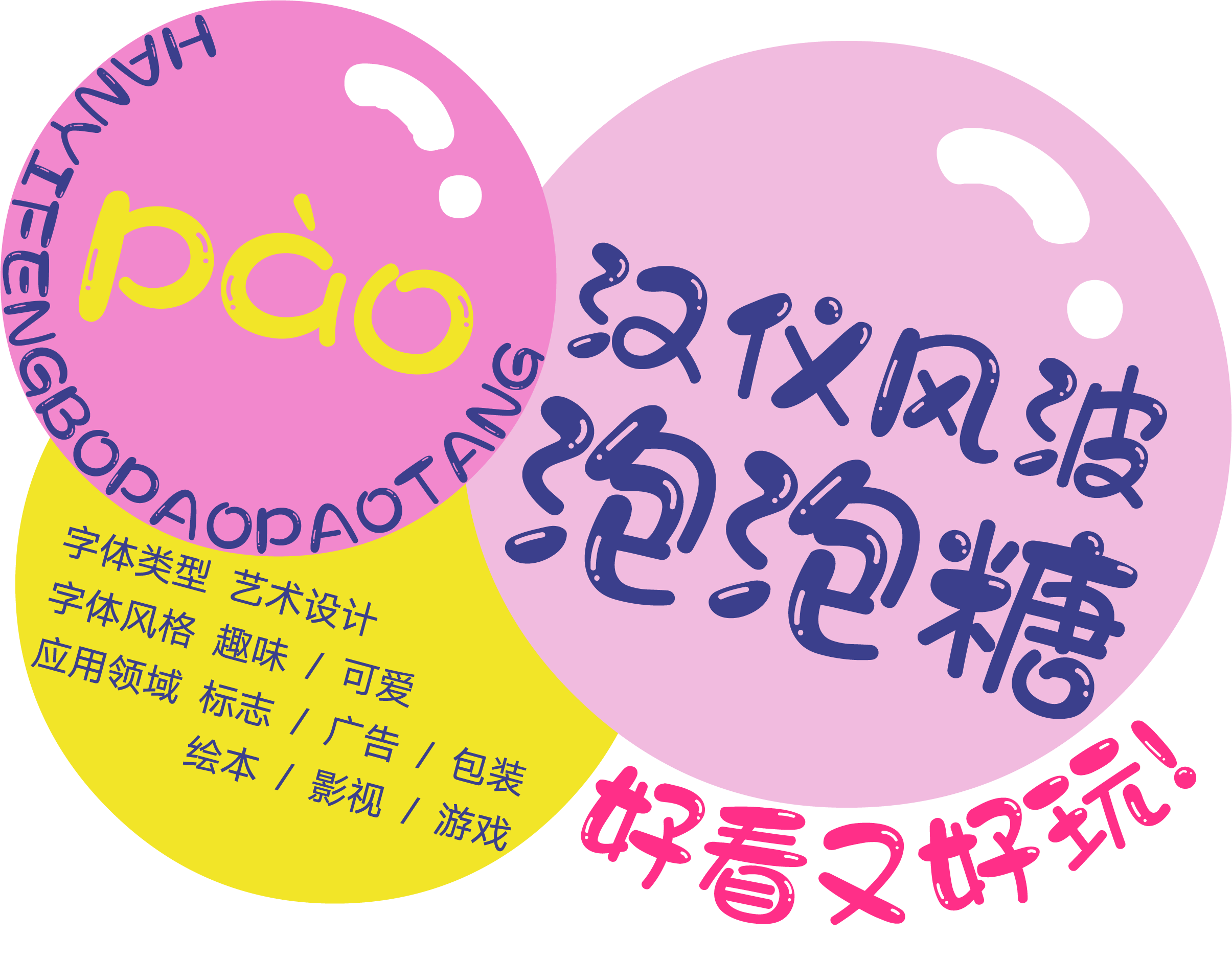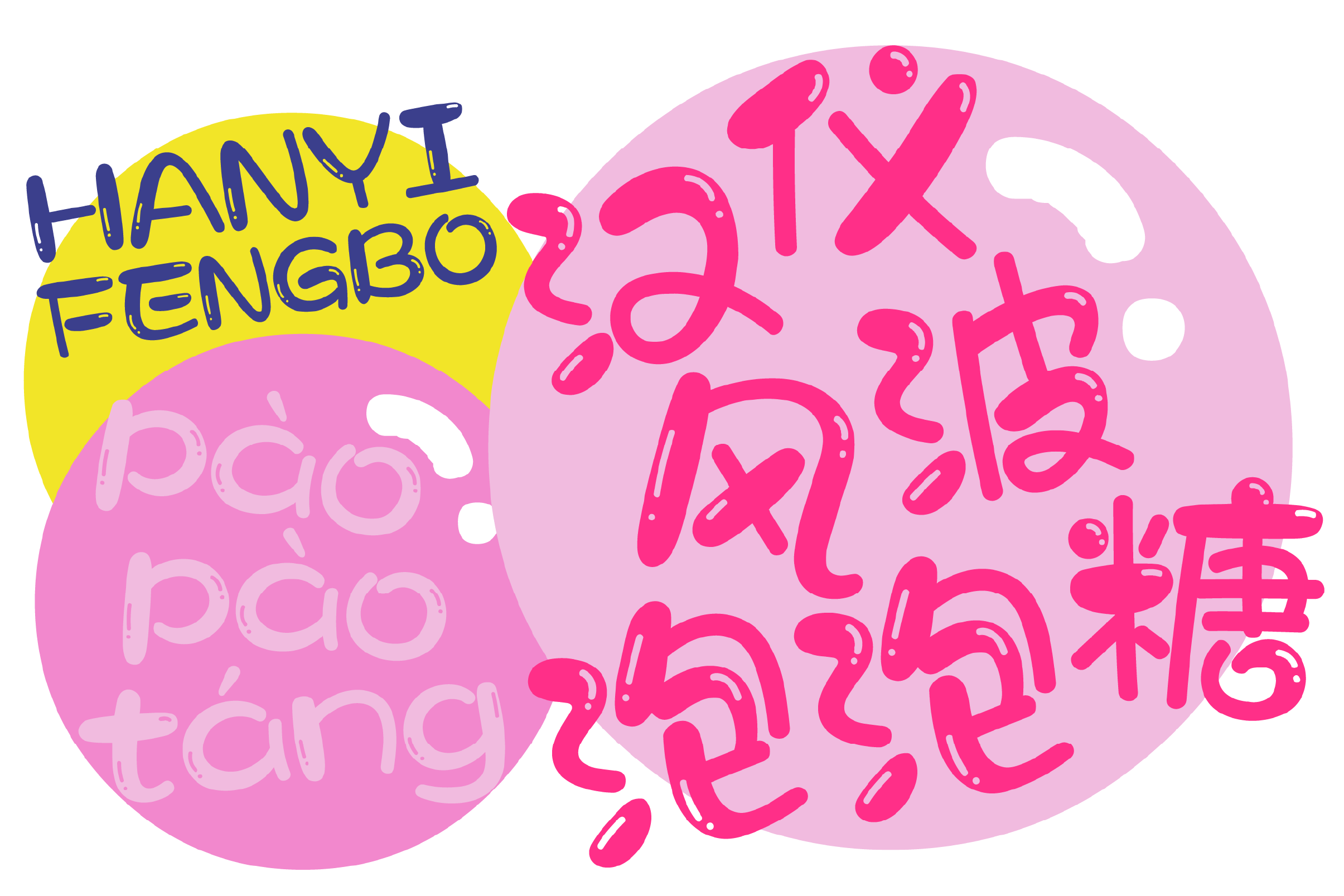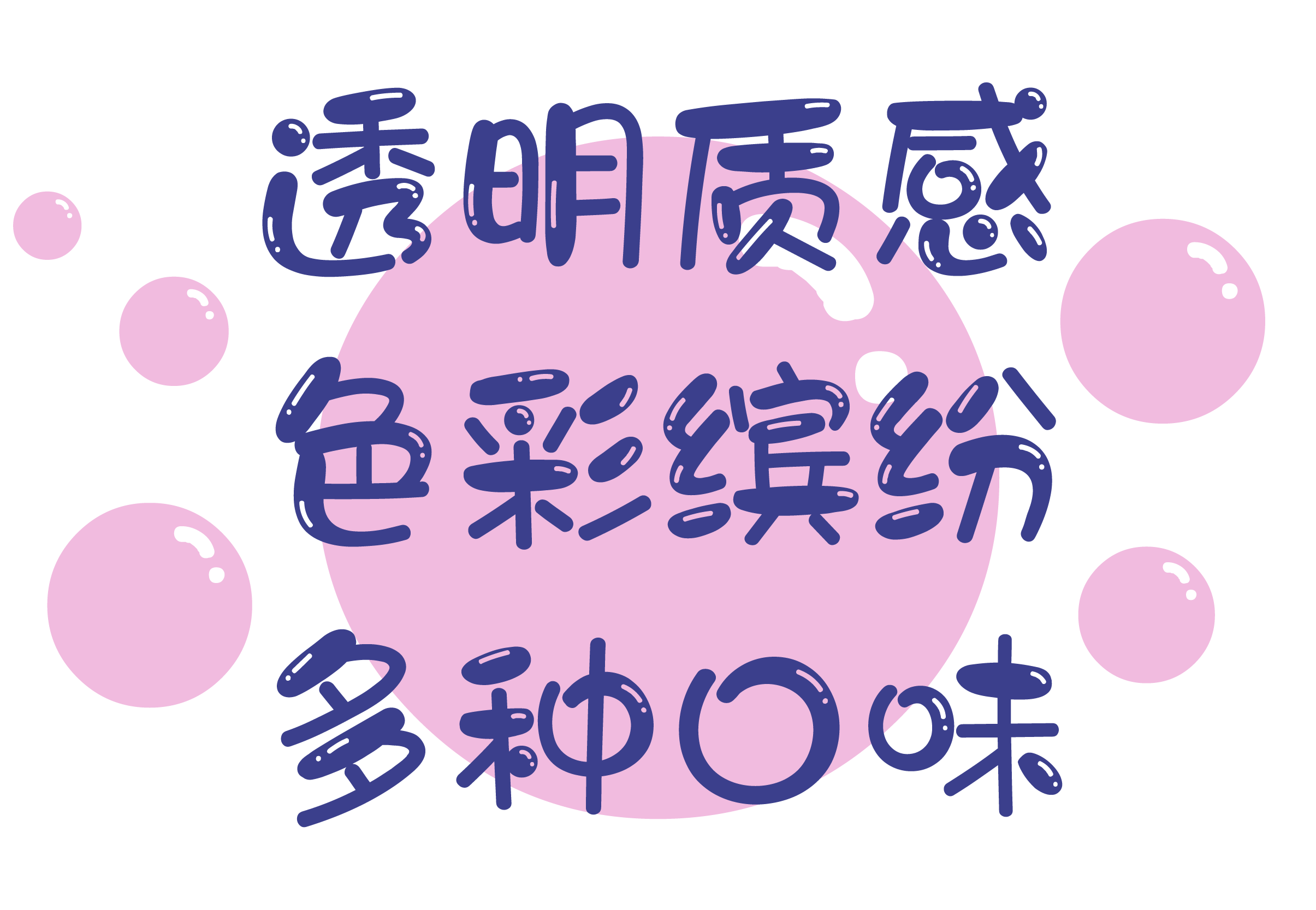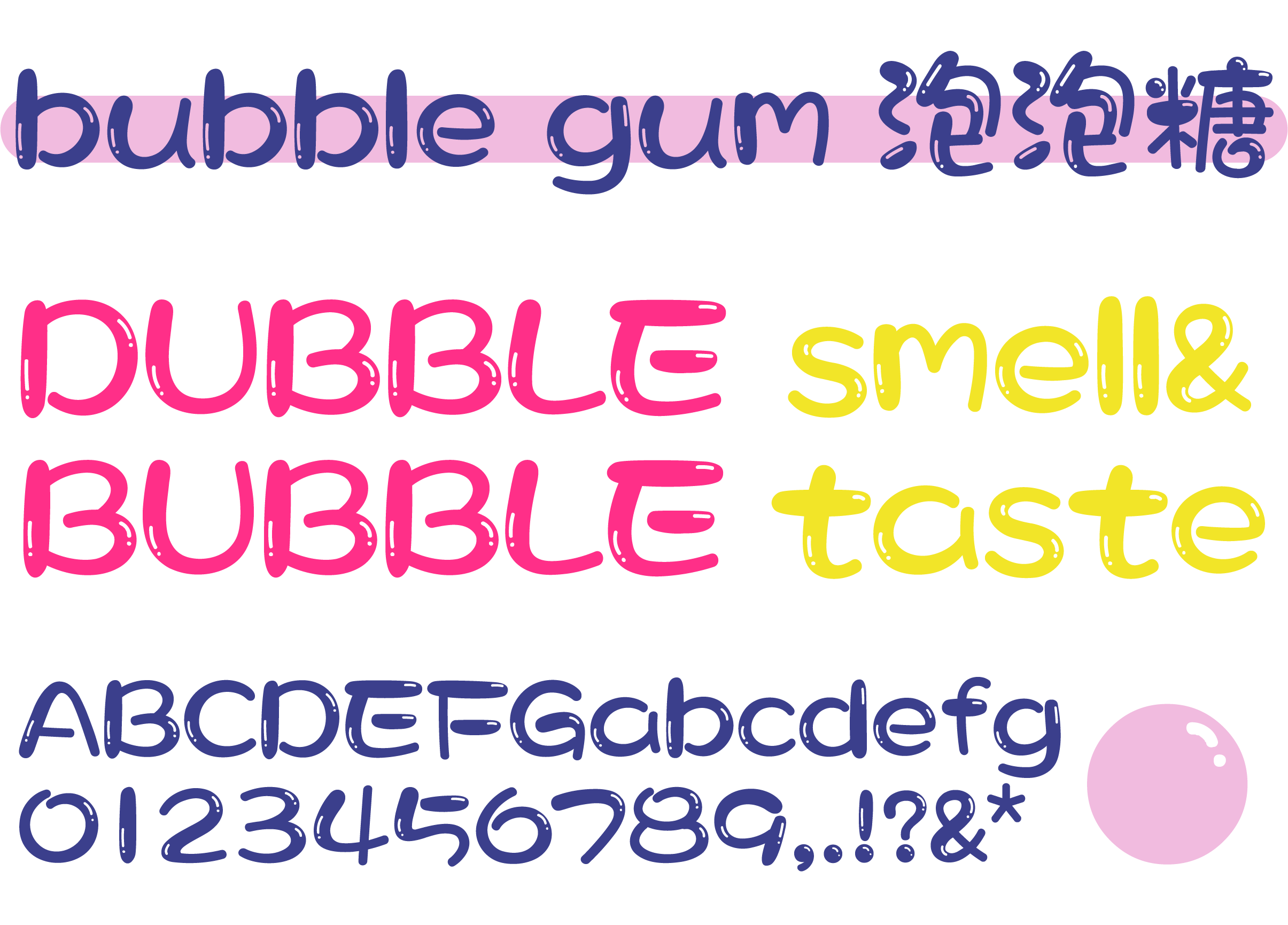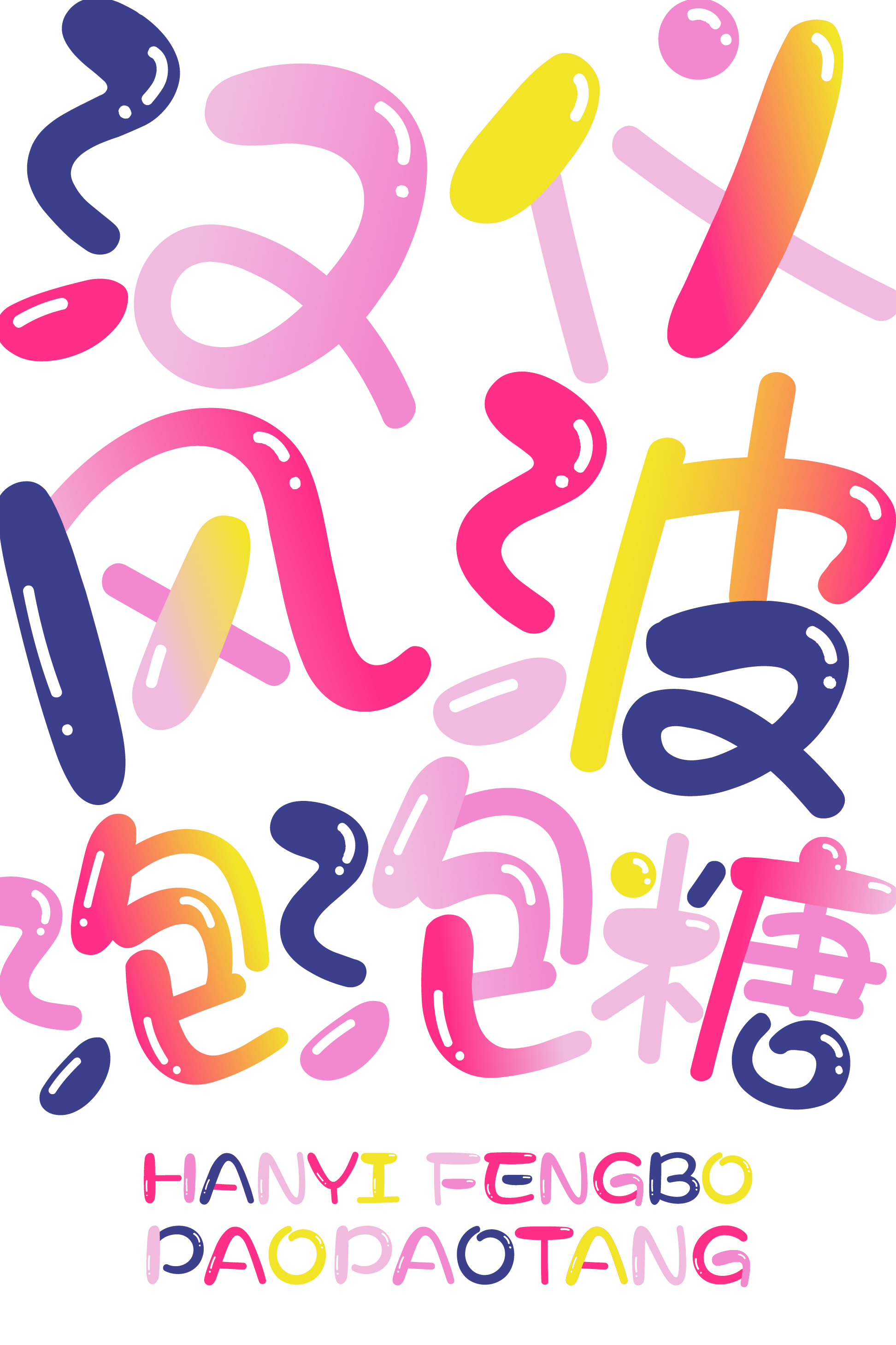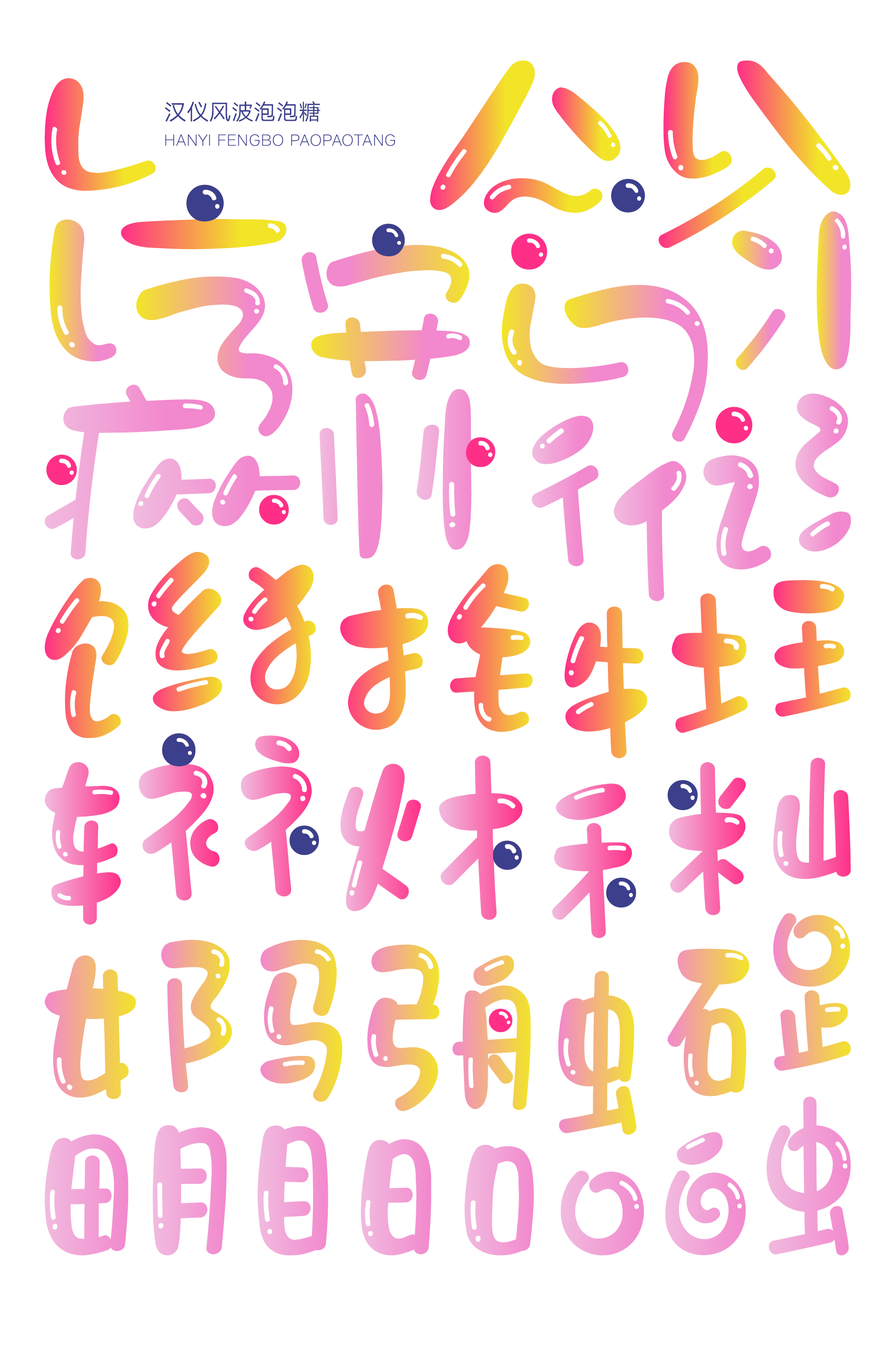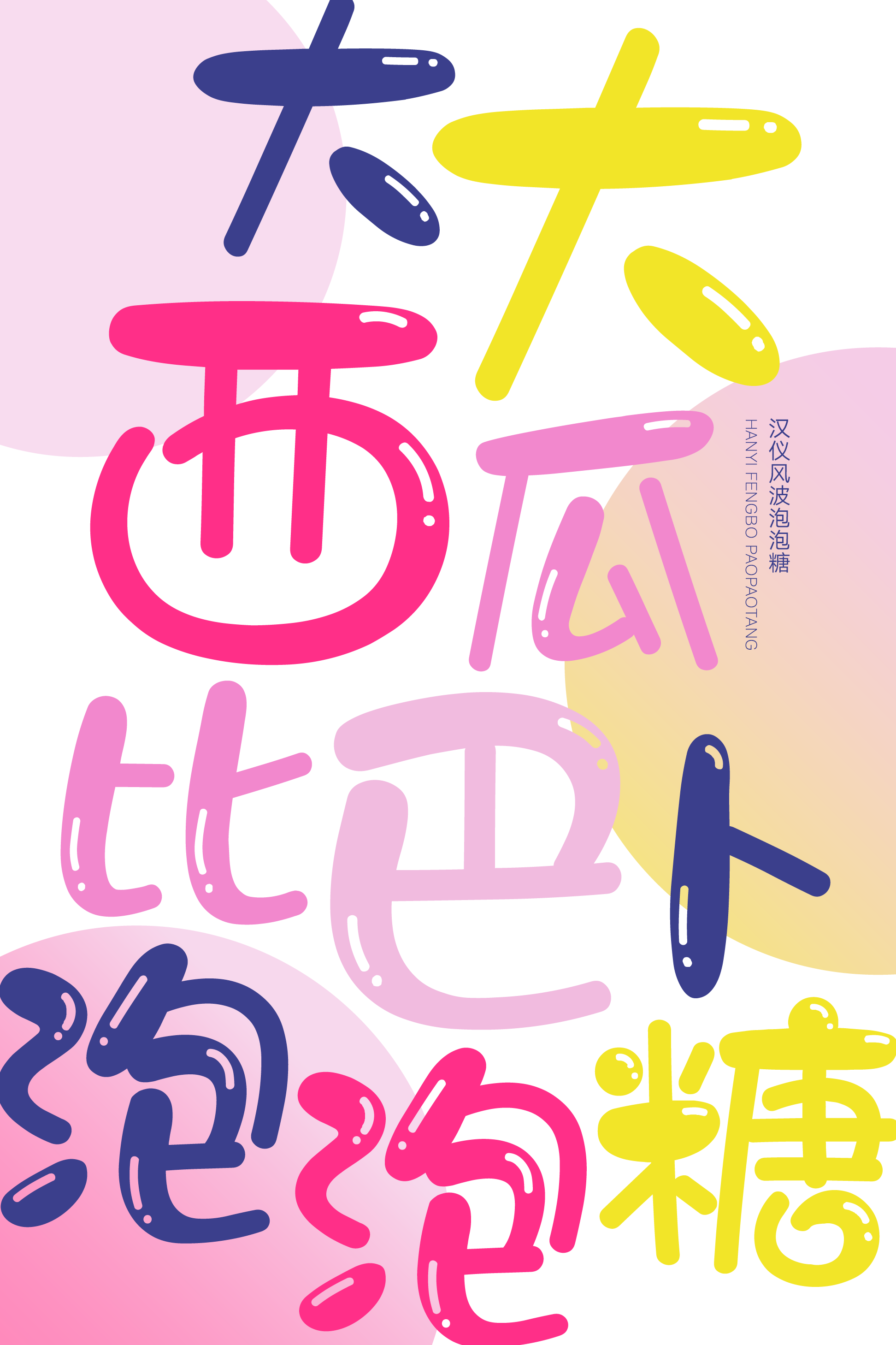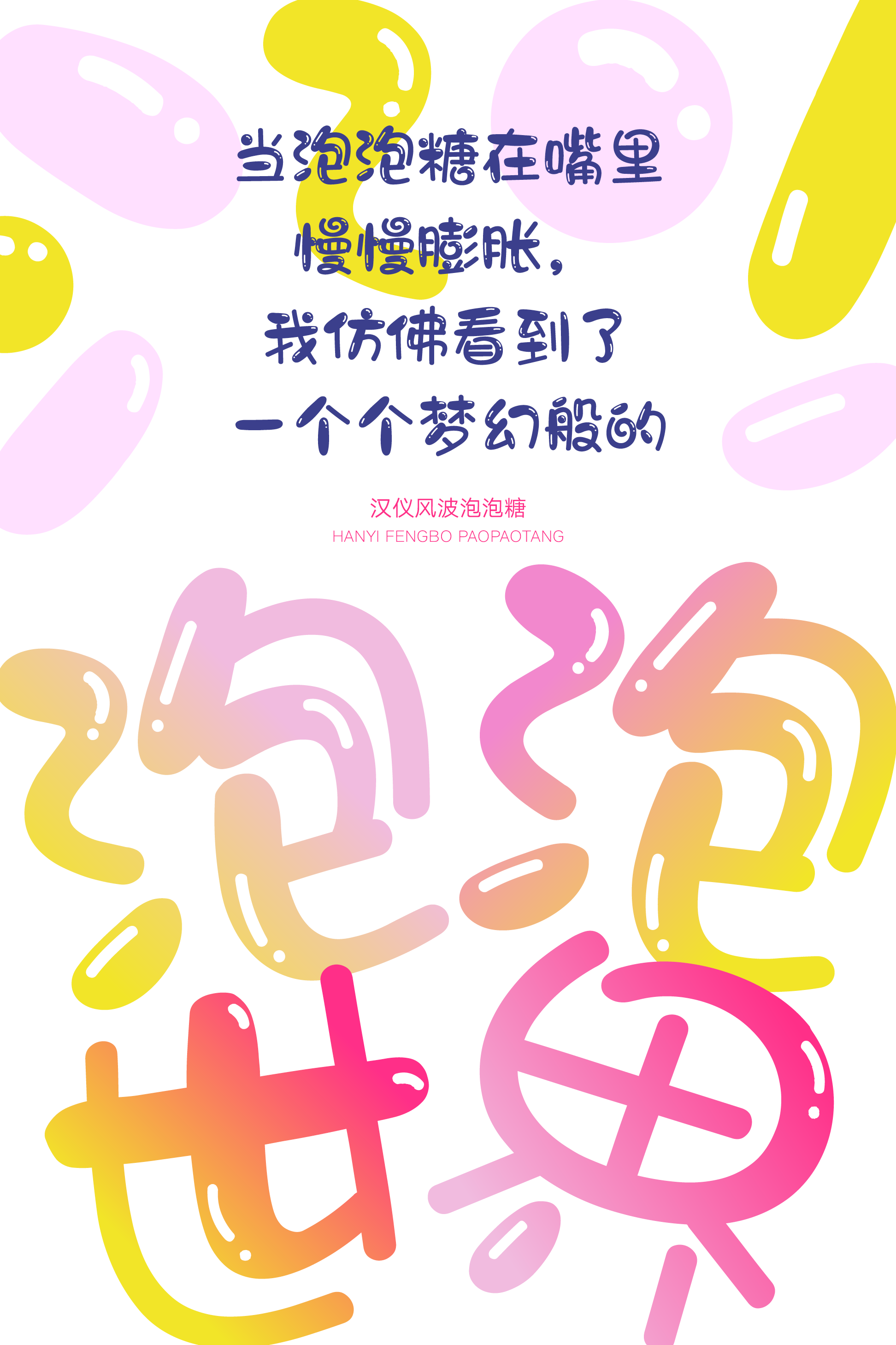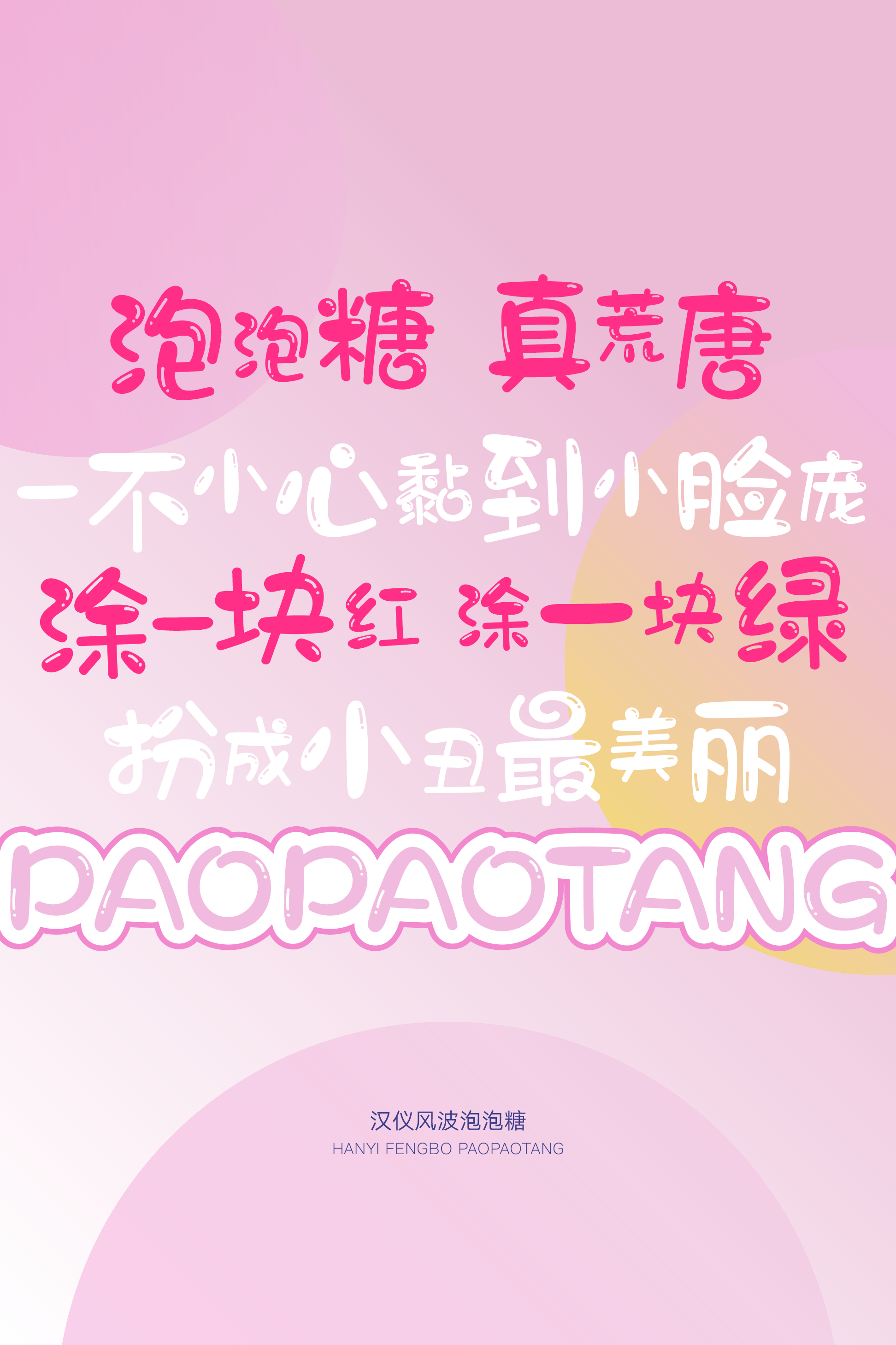
一款好看又好玩的标题字
汉仪风波泡泡糖,好看又好玩!字形圆润饱满,笔画富有弹性,再加上笔画的高光点缀,看起来就像是泡泡糖一样的质感,可以吹出又大又圆的泡泡,乐趣满满。这款字体由汉仪签约作者梁风波创作,是一款颇具趣味性和装饰性和创意标题字体,适用于休闲娱乐、食品包装、电商广告等各类使用场景,让整个画面活泼起来。
字形圆润饱满,像是吹出大大的泡泡。
笔画富有弹性,连带处理趣味十足。
高光点缀笔画,还原了泡泡糖的质感。
隐藏玩法:手动去掉高光,获得另一款扁平字体。
西文部分同样是圆圆的造型、弹弹的线条,再点缀高光,中西文搭配使用,吹出双倍又大又圆的泡泡。